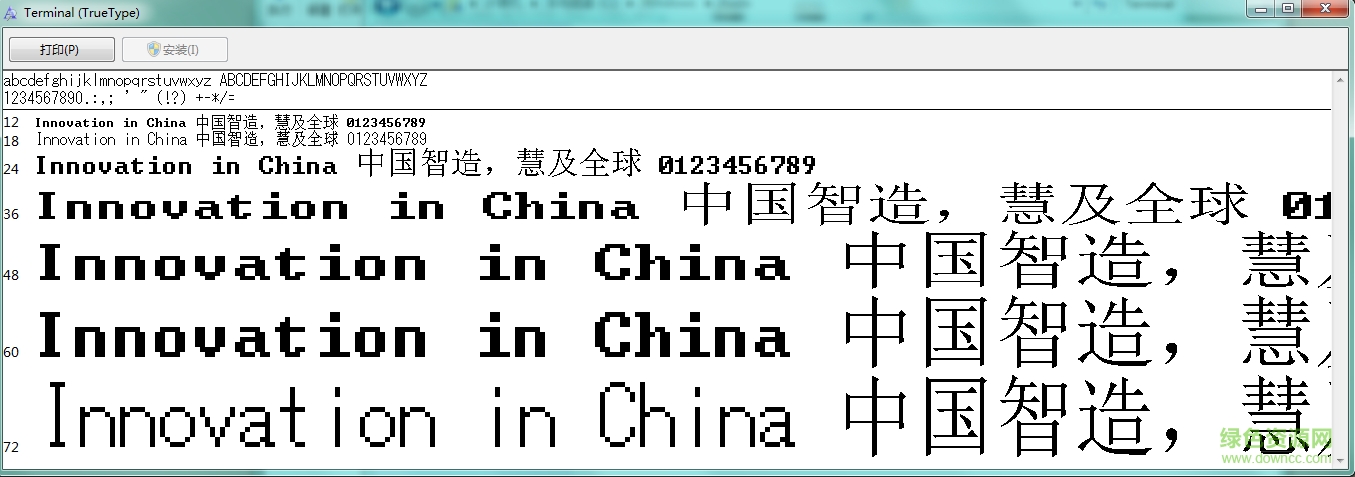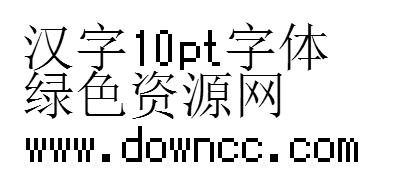
漢字10pt是一款常用的漢字字體,造型精簡(jiǎn)筆觸正直,有著干練的外觀和舒適的視覺呈現(xiàn),很多朋友都在找這款字體,今天來綠色資源網(wǎng)即可免費(fèi)下載使用哦!
漢字10pt是個(gè)v開頭的文件,打開以后標(biāo)題是Terminal,憑證字體用Word9.5號(hào)字就行了。綠色資源網(wǎng)為大家?guī)鞹erminal字體下載。